Как использовать необычные шрифты в Instagram
Кратко: Можно добавлять «необычные» шрифты в био, подписи и комментарии Instagram, копируя символы Unicode из внешних приложений или сайтов. Это не меняет системный шрифт Instagram, но визуально оживляет текст; проверяйте читаемость и совместимость устройств.
Как работают кастомные шрифты в Instagram
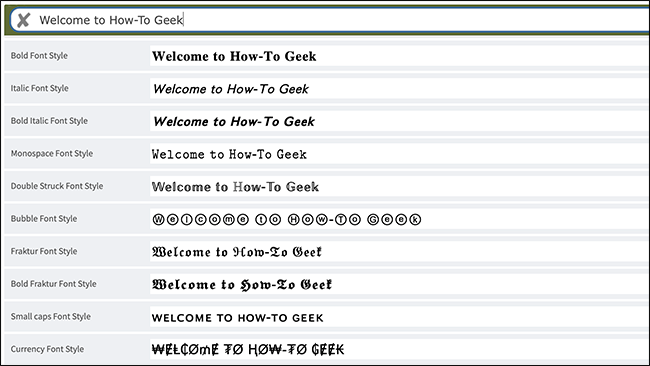
Instagram использует шрифт Proxima Nova для мелкого текста — комментариев и подписей. Нельзя «сменить» этот системный шрифт в приложении, но можно обойти ограничение, используя другие символы из набора Unicode.
Короткое определение: Unicode — международный стандарт кодирования символов; он включает буквы, диакритические знаки, математические символы, буквы из разных алфавитов и декоративные варианты букв.
Через Unicode можно получить стили, которые выглядят как курсив, рукописный шрифт, готический набор или круглые буквы: 𝒶 𝔞 ⓛ. Комбинируя такие глифы, получают визуальные эффекты вроде текста вверх ногами (ʇuoɟ uʍop ǝpısdn).
Важно: Instagram поддерживает большинство скриптов Unicode, но отображение зависит от устройства и версии операционной системы. Некоторые символы могут выглядеть иначе или вовсе не отображаться на старых устройствах.
Как добавить необычные шрифты в подписи и био
Самый простой способ — использовать веб‑сервис или приложение, которое преобразует обычный текст в набор Unicode‑символов и даёт готовые варианты для копирования.
Шаги, кратко:
- На смартфоне или компьютере откройте сайт типа CoolFont.org или аналогичный конвертер Unicode.
- Вставьте или введите нужный текст (имя, подпись, комментарий).
- Выберите вариант шрифта из предложенных — от аккуратных до декоративных.
- При желании нажмите кнопку украшений (например, «Decorate»), чтобы добавить символы‑декораторы: сердца, звёздочки, рамки.
- Нажмите «Copy» или используйте выделение -> копировать.
- Вставьте текст в поле био, подписи поста или комментария в Instagram.
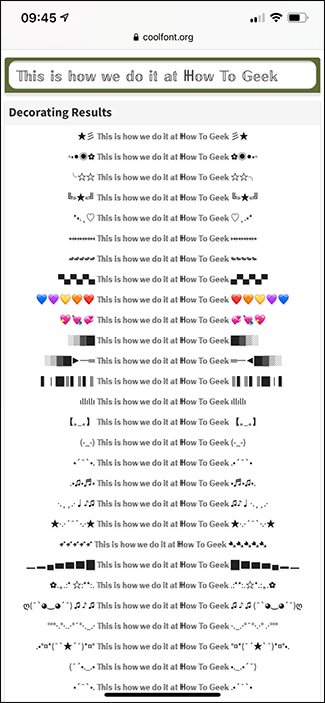
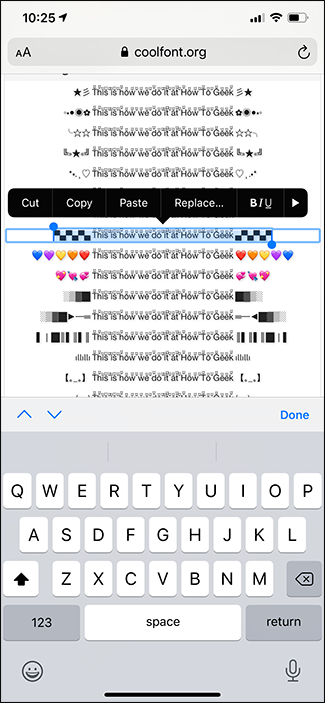
Такой же метод работает для историй, но встроенные шрифты сторис обычно выглядят чище и лучше масштабируются.
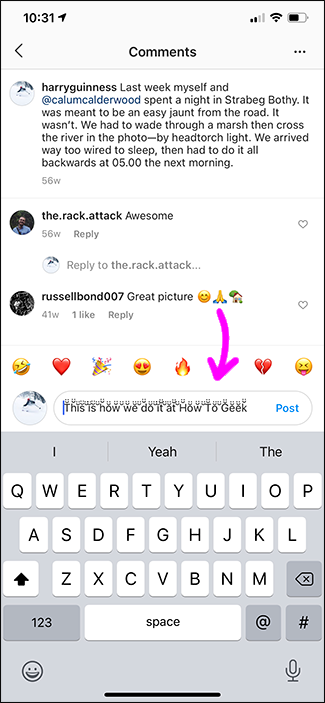
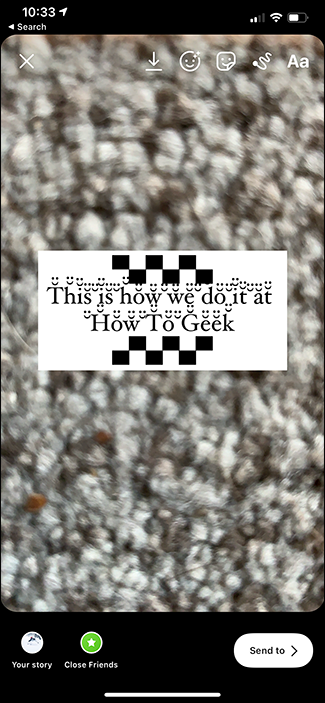
Когда это не сработает
- Старые версии Android/iOS или редкие устройства могут не поддерживать декоративные глифы — текст будет выглядеть как странные квадраты или пробелы.
- Автоматические проверки платформы (поиск, хэштеги) ориентируются на обычные символы: необычные шрифты могут ухудшать индексируемость и поиск по ключевым словам.
- Скринридеры и пользователи с ограничениями зрения могут испытывать трудности с чтением декоративного текста — это влияет на доступность.
Альтернативные подходы
- Использовать встроенные шрифты Instagram для историй — безопасно и консистентно на всех устройствах.
- Установить стороннюю клавиатуру с декоративными символами (если доверяете разработчику).
- Встраивать текст как часть изображения (на фото или шаблоне) — полный контроль над типографикой, но текст уже не копируем.
Ментальные модели и правила выбора
- Правило читабельности: декоративный шрифт — акцент, не основной текст. Если сообщение важное, используйте стандартный текст.
- Правило совместимости: если аудитория широкая, тестируйте на Android и iOS и на старых моделях.
- Правило бренда: используйте декоративные символы в пределах фирменного стиля; не переусердствуйте.
Мини‑методология: быстрый рабочий процесс
- Определите цель: привлечение внимания / визуальный акцент / игра слов.
- Подберите 2–3 варианта в конвертере и сравните в черновике Instagram.
- Проверяйте вид на телефоне и в веб‑версии Instagram.
- Сохраняйте выбранный вариант в заметках для повторного использования.
Чеклист по ролям
Контент‑креатор:
- Выбрал 1–2 варианта шрифта для серии постов.
- Проверил читаемость на iOS/Android.
- Убедился, что текст читается без искажений в превью ленты.
SMM‑менеджер:
- Проверил влияние декоративного текста на поисковые запросы и хэштеги.
- Согласовал стиль с руководителем бренда.
- Подготовил запасной вариант для адаптивности.
Комьюнити‑менеджер:
- Избегает декоративного текста в важных сообщениях и ответах.
- Использует необычные шрифты для лёгких, развлекательных комментариев.
Рекомендации по доступности и безопасности
Важно: используйте декоративные символы экономно. Добавляйте альтернативный простой текст в описании изображений (alt‑текст) и в первом предложении подписи, чтобы пользователи со скринридерами понимали суть публикации.
Краткое резюме
- Вы не можете сменить системный шрифт Instagram, но можете использовать Unicode‑символы для декоративного текста.
- Метод прост: конвертируете текст, копируете и вставляете; проверяйте совместимость на разных устройствах.
- Альтернатива — встроенные шрифты сторис или текст в изображениях, если важна полная типографическая контроль.
Примечание: этот подход применим и к другим платформам, поддерживающим Unicode (Twitter, Facebook). Всегда проверяйте читаемость и доступность перед публикацией.